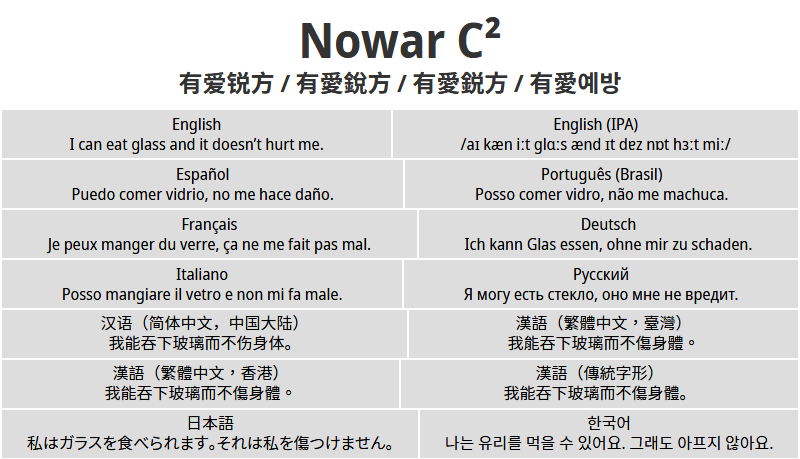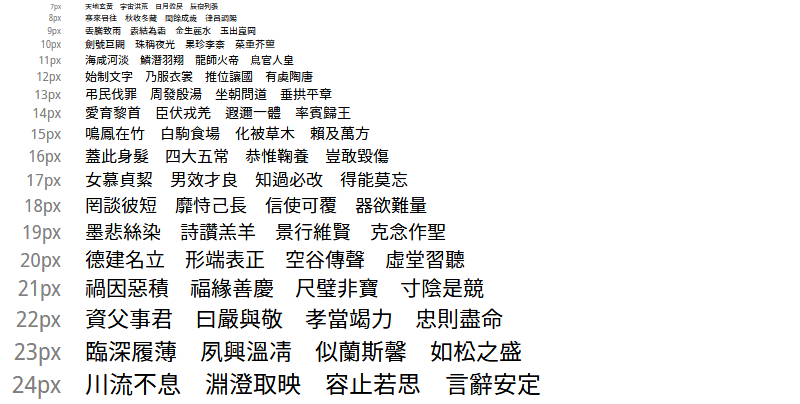
有爱锐方(NowarC²)是专为《魔兽世界》和《魔兽世界:经典怀旧服》设计的一款可免费商用的中文字体包,也可以叫有爱魔兽锐方。是通过字形微调技术,让文字边缘比普通字体看起来更加清晰锐利,从而提高文字可读性,以适应游戏界面等需要长时间注视且动态画面较多的场景。
有爱锐方提供 ExtraLight(极细)、Light(细)、Regular(常规)、Medium(中等)、Bold(粗) 5 种字重;拥有 CN(简体中文)、TW(繁体中文)、KR(韩文)等在内的 9 种地区变体,可以满足不同场景、不同语言环境下的排版需求和字形规范。除了在《魔兽世界》游戏中经常看到外,有爱锐方还特别适合海报、广告、电商设计等需要清晰锐利风格的场景。